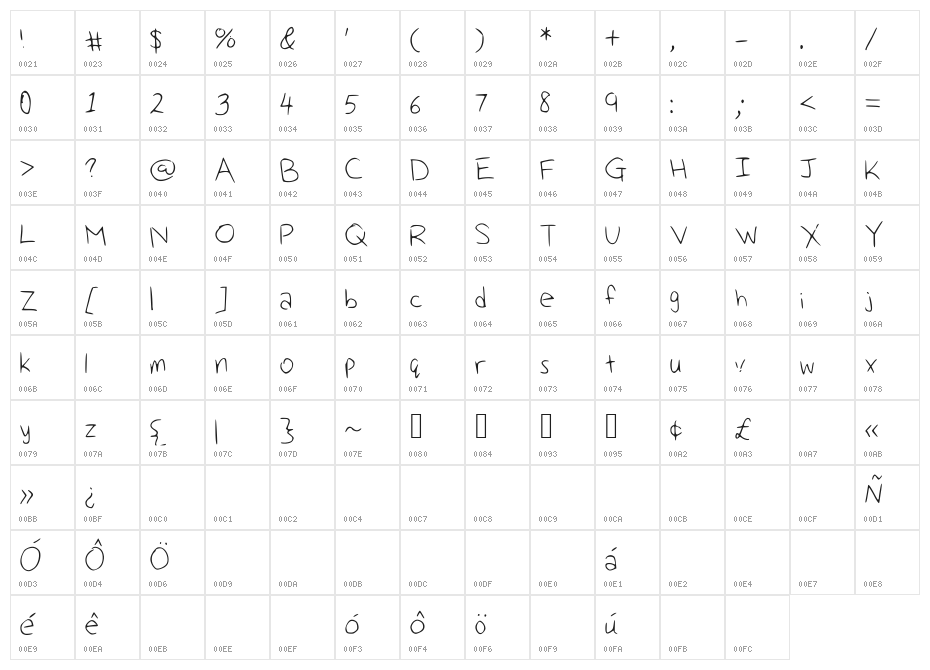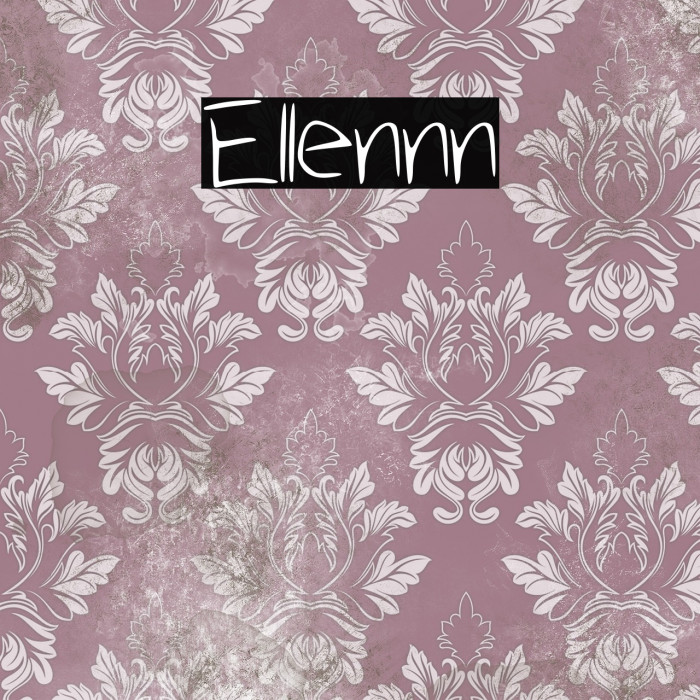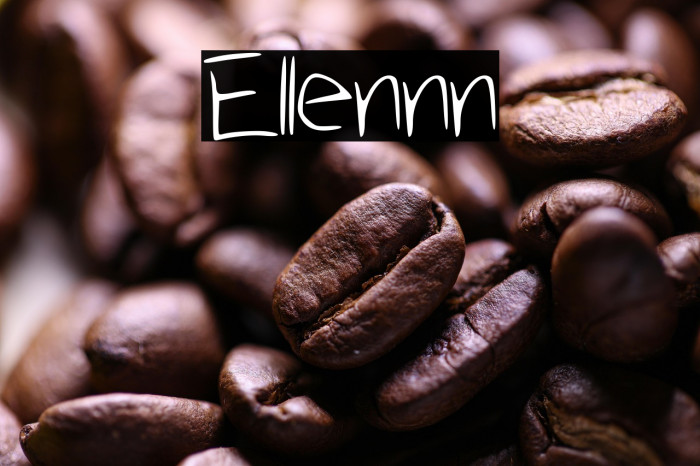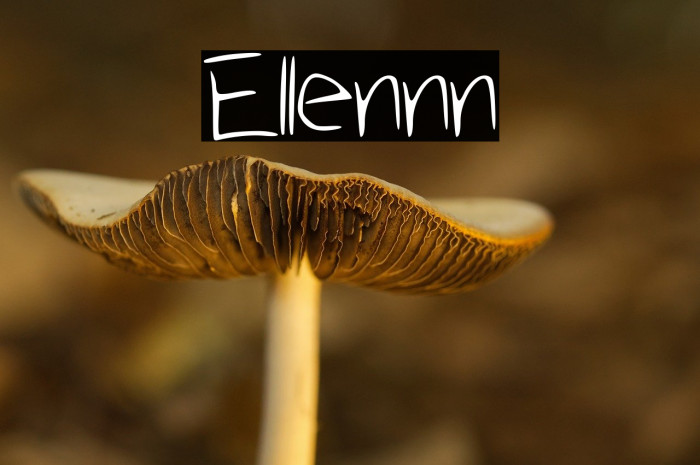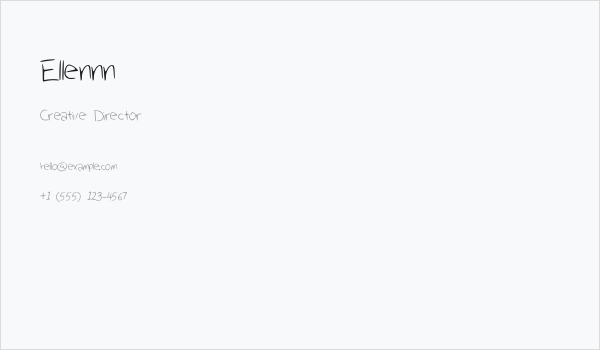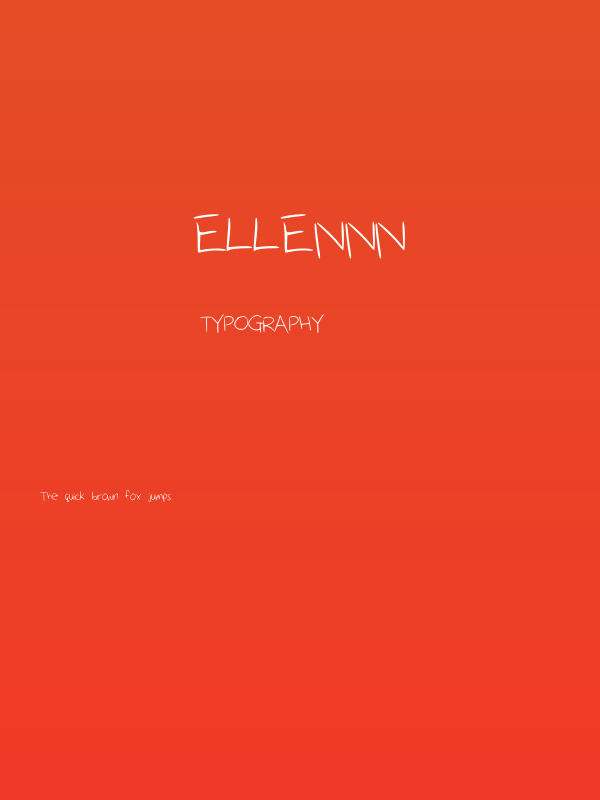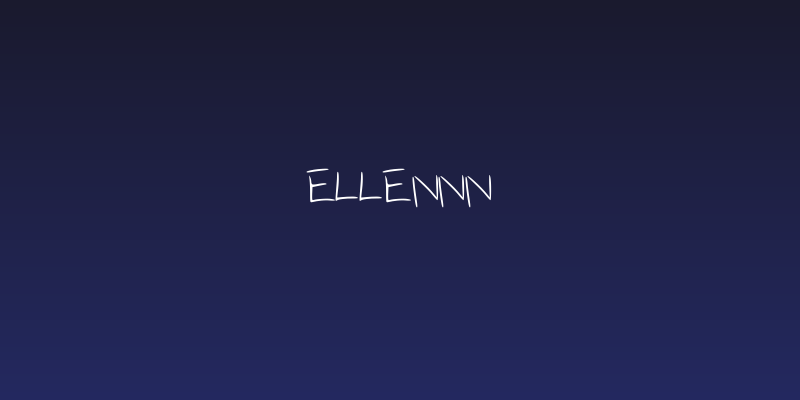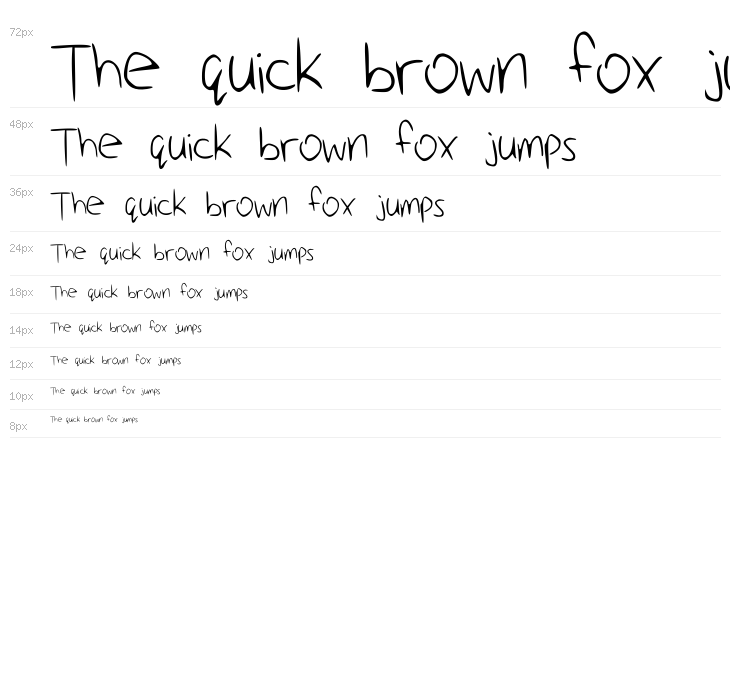
Ellennn Font
| Gesamtstil | Casual |
| Anwendungsfall | Logos, Headlines, Informal text |
| Vorgeschlagene Projekte | Ideal for personal notes, greeting cards, casual invitations, and playful branding projects. |